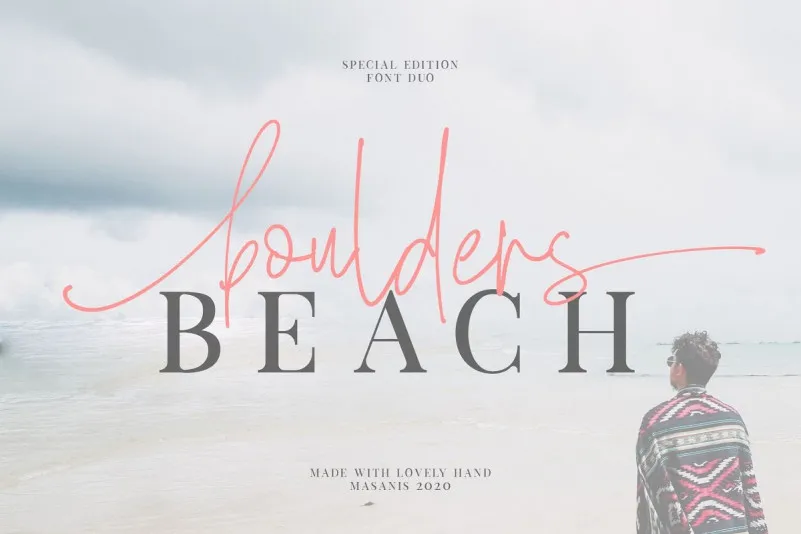
Boulders Beach Script Font – Download Grátis
Descubra Boulders Beach Script Font, uma escolha ideal para seus próximos projetos criativos. Ideal para logos, convites, papelaria e até mesmo para criações especiais para eventos, esta fonte é perfeita graças ao seu estilo natural e elegante. Confeccionada a partir de traços escritos a mão com um canetão Gel, Boulders Beach Script transmite uma sensação de confiabilidade e elegância que o torna indispensável em várias aplicações. Seja para logotipos modernos, convites elegantes, ou até mesmo como fonte para imagens e produtos impressos – esta font é uma opção versátil para qualquer projeto visual. Com sua beleza única e seu uso natural, você certamente irá adorar explorá-la.